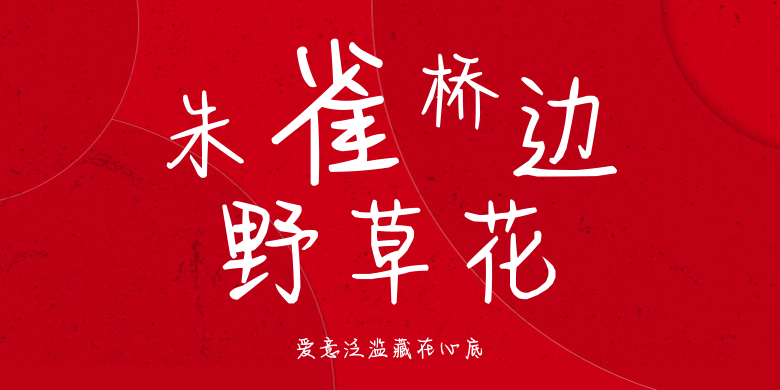
爱意泛滥藏在心底
爱意泛滥藏在心底,这款字体结构工整、笔画清晰,兼顾美观与易读性,适用于标题、正文、海报、包装、LOGO 等多种场景。字形优雅稳定,风格百搭耐看,适配日常排版与创意设计,让文字呈现更舒适、更具质感。爱意泛滥藏在心底一笔一画,皆是细节,以均衡的比例、流畅的线条打造舒适视觉体验,字形端正大气,风格简约现代。无论是商业设计、品牌宣传还是日常排版,都能轻松驾驭,让文字更有格调与力量。爱意泛滥藏在心底字体下载。